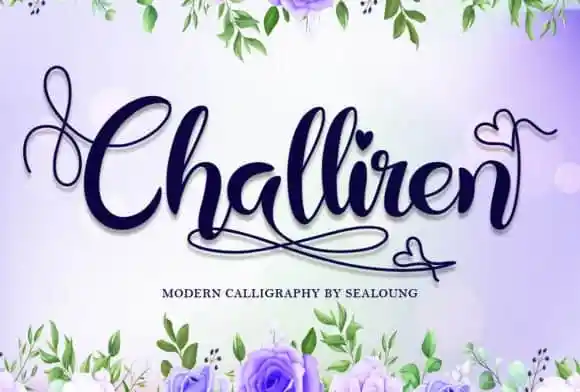
Challiren Calligraphy Font – Download Grátis
A fonte Challen Calligraphy Font é uma escolha perfeita para quem busca dar um toque sofisticado a qualquer projeto visual. Esta elegante fóntica moderna, criada pelo Designer 99designs e inspirada no belo clima da antiguidade, adicionará uma atmosfera romântica ao seu próximo trabalho de design gráfico. Perfeita para aplicar em cartões de convidações, headlines ou qualquer tipo de layout que exija um toque refinado, essa fonte de escritura é versátil e extremamente atraente. Seu design moderno com base em fónticas tradicionais garante uma aparência impecável e sofisticada, tornando-a uma excelente opção para aqueles buscando dar brilho à sua próxima criação visual. Não importa o projeto que você está trabalhando, essa fonte Challen Calligraphy é certamente a escolha perfeita para adicionar um toque elegante e único.